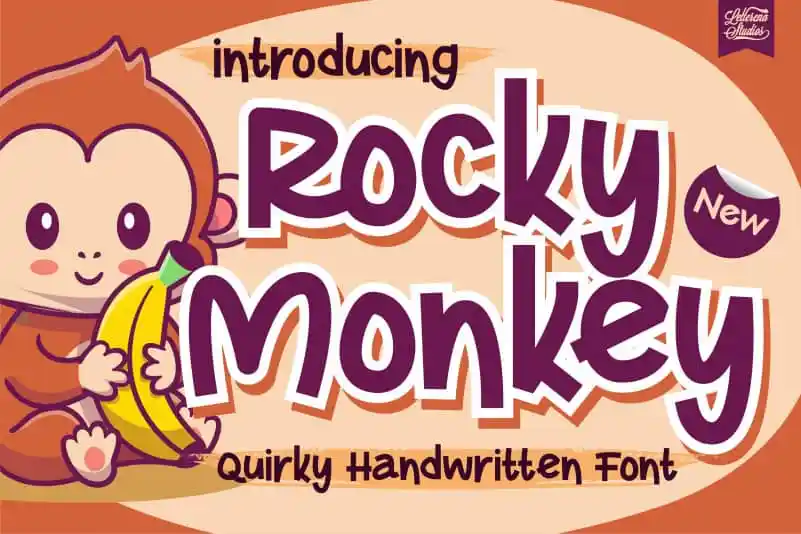
Rocky Monkey Display Font – Fonte Grátis
Rocky Monkey Display Font
A Rocky Monkey Display Font é uma fonte de display cheia de personalidade ideal para projetos criativos. Ela traz ao seu trabalho um toque de brasilidade com sua vibe divertida e irreverente, perfeitamente adaptada para crianças. A fonte é especialmente apropriada para temas infantis, e combina bem com cores vivas e vibrantes para criar um design único e alegre. Seja para cartões personalizados ou decoração de festa temática, ela trará brilho à sua criação. Perfect para designers, essa fonte é uma ótima opção se você está buscando algo que dê vida aos seus projetos DIY em um toque. Não perca a chance de fazer suas próprias obras de arte com esse charmoso e divertido desenho tipográfico!